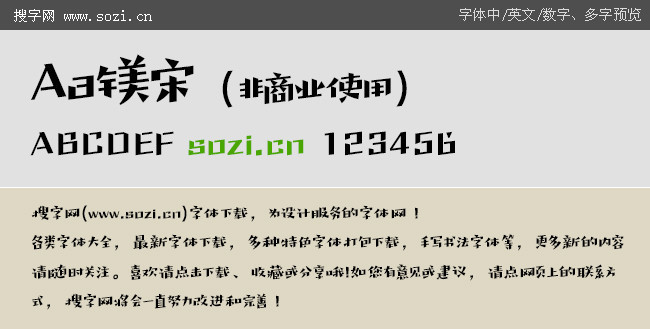
Aa鎂宋
搜字網(wǎng)給大家提供一款A(yù)a鎂宋(非商業(yè)使用)中文字體下載,該字體是一款帶有宋體風(fēng)格的藝術(shù)字體,字形充滿(mǎn)個(gè)性,趣味性十足,具有很好的視覺(jué)感。適合書(shū)裝設(shè)計(jì)、包裝設(shè)計(jì)、海報(bào)設(shè)計(jì)等應(yīng)用(此字體為個(gè)人非商用版,商用可以聯(lián)系QQ:1006760504)。